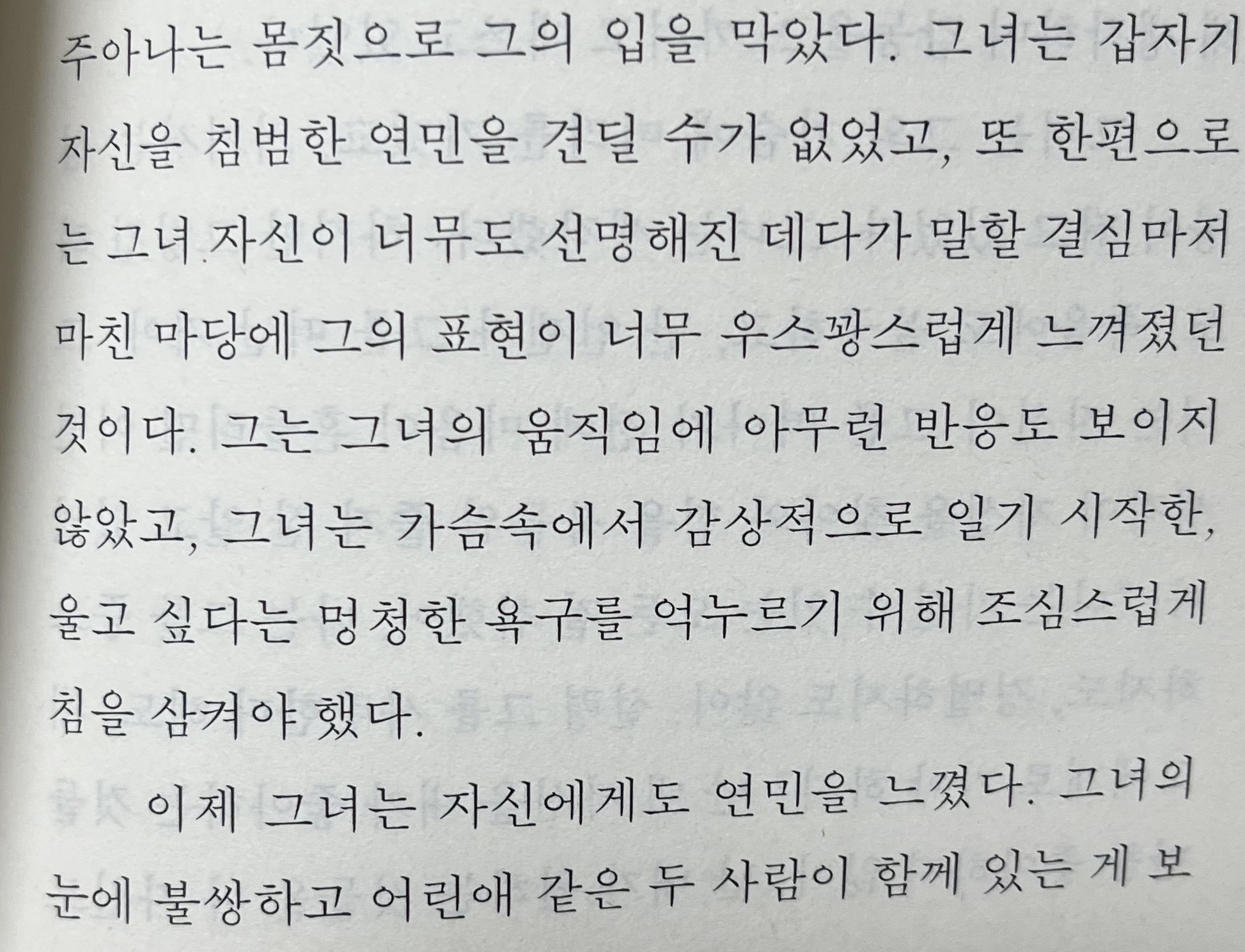
본문 서체 궁금합니다
<야생의 심장 가까이>라는 책을 읽는데 서체가 예뻐서 질문드립니다.
첨부한 이미지 중간에 보시면 '표현'의 'ㅛ' 모음이 중앙으로 모여 있는 형태가 특징인 듯 한데
검색을 해봐도 잘 찾지 못하여 질문드립니다!
<야생의 심장 가까이>라는 책을 읽는데 서체가 예뻐서 질문드립니다.
첨부한 이미지 중간에 보시면 '표현'의 'ㅛ' 모음이 중앙으로 모여 있는 형태가 특징인 듯 한데
검색을 해봐도 잘 찾지 못하여 질문드립니다!
우아 폰트이쁘네요
SM3세명조 같습니다.